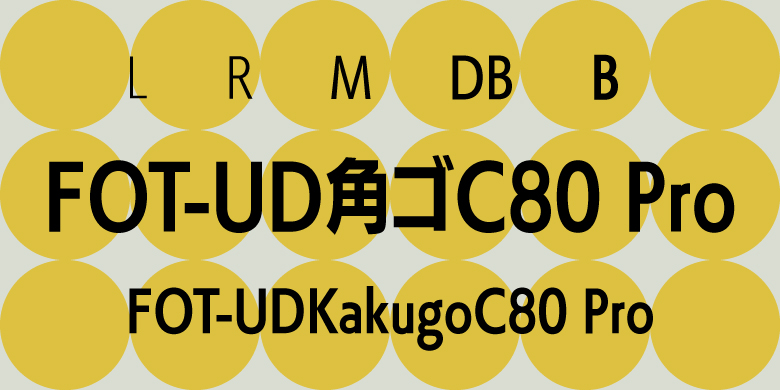
FOT-UDKakugoC80 Pro家族,这款字体结构工整、笔画清晰,兼顾美观与易读性,适用于标题、正文、海报、包装、LOGO 等多种场景。字形优雅稳定,风格百搭耐看,适配日常排版与创意设计,让文字呈现更舒适、更具质感。FOT-UDKakugoC80 Pro家族一笔一画,皆是细节,以均衡的比例、流畅的线条打造舒适视觉体验,字形端正大气,风格简约现代。无论是商业设计、品牌宣传还是日常排版,都能轻松驾驭,让文字更有格调与力量。FOT-UDKakugoC80 Pro家族字体下载。
"UD角ゴ_ラージ" 以80%的长体设计,用于在有限的空间中美观且易于阅读地显示大量文字信息,特别适合小尺寸的各种详细显示。